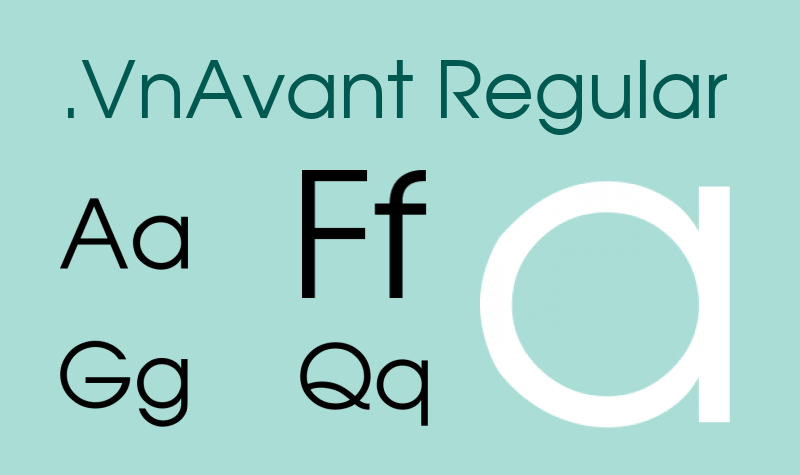
Font Vnavant Việt Hóa
Việt hóa: Đã Việt Hóa
Bộ Font: VNAvant
Phân loại: Hiện đại
Font VNAvant Việt Hóa là một sự lựa chọn tinh tế và hiện đại, thường được sử dụng trong các thiết kế đòi hỏi sự rõ ràng và tính thẩm mỹ cao. Với kiểu dáng gọn gàng và đường nét thanh mảnh, VNAvant phù hợp cho cả văn bản chính và tiêu đề, mang đến vẻ ngoài chuyên nghiệp và dễ đọc. Đặc biệt, phông chữ này thuộc bộ Font Chữ Không Chân có thể thích hợp với nhiều loại dự án thiết kế khác nhau, từ tài liệu in ấn, website, đến các ấn phẩm quảng cáo, giúp bạn tạo ra một sản phẩm thị giác hài hòa và thu hút.